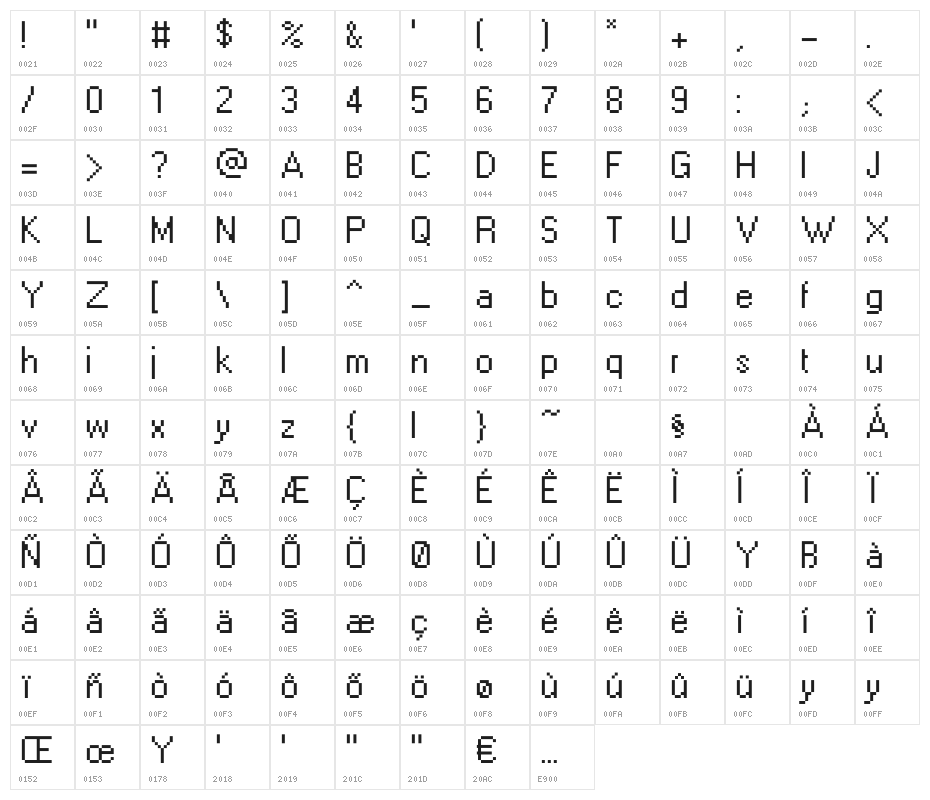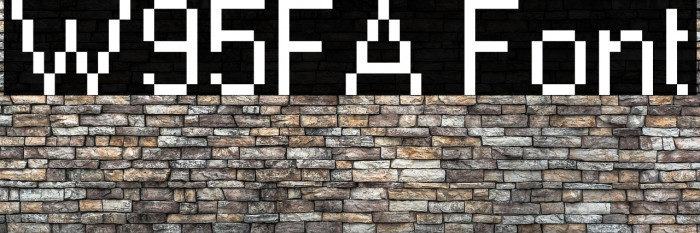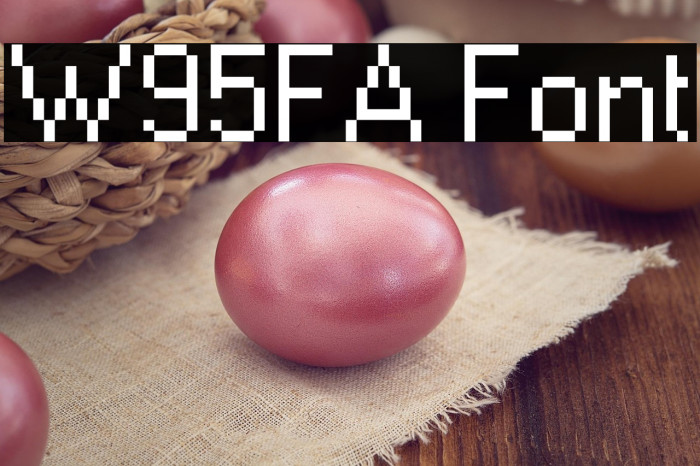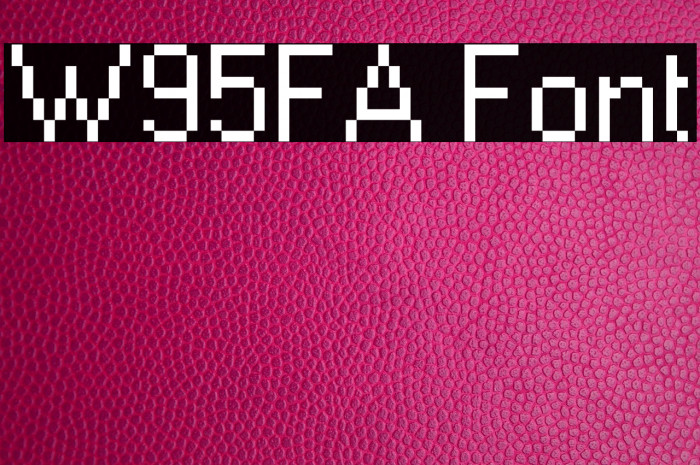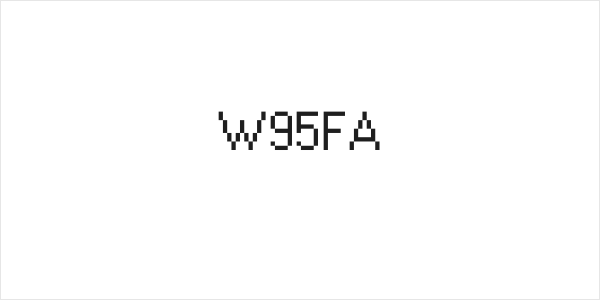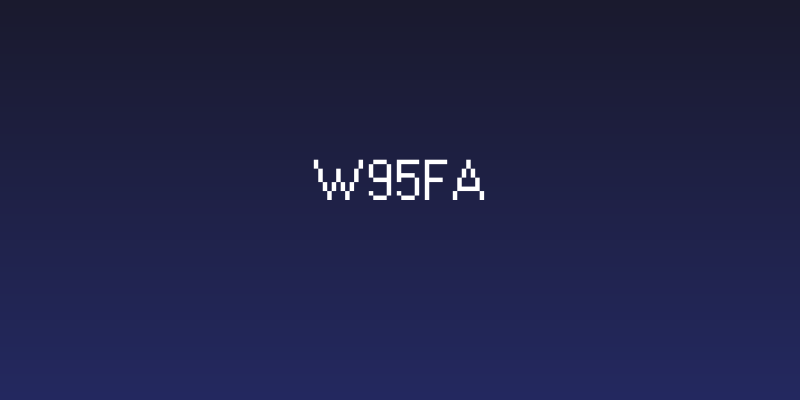
W95FA Font
| Gesamtstil | Vintage |
| Anwendungsfall | Logos, Headlines, Digital Art |
| Vorgeschlagene Projekte | Ideal for retro video game graphics, digital art projects, or any design that seeks to capture the essence of early computing aesthetics. |